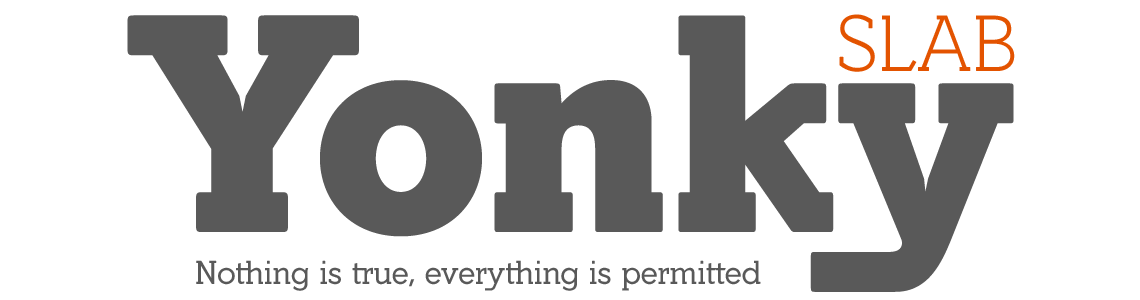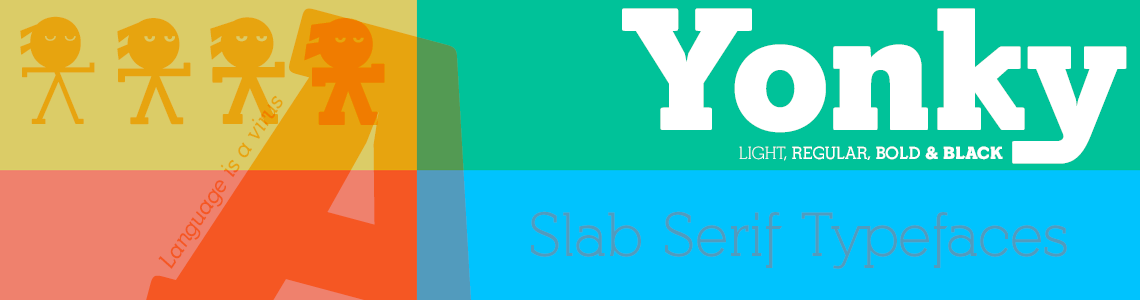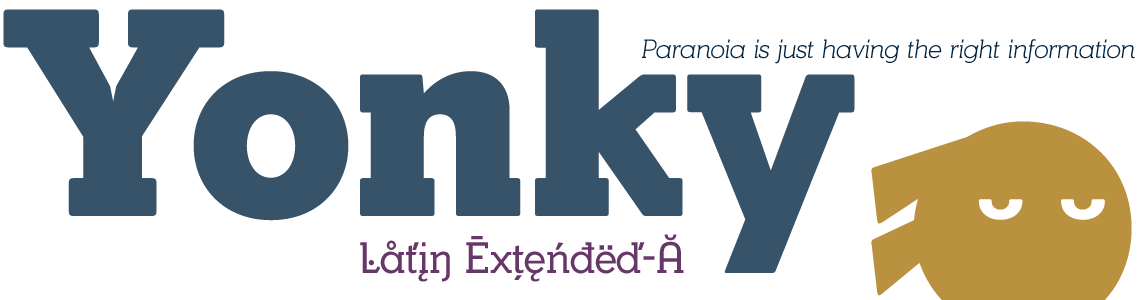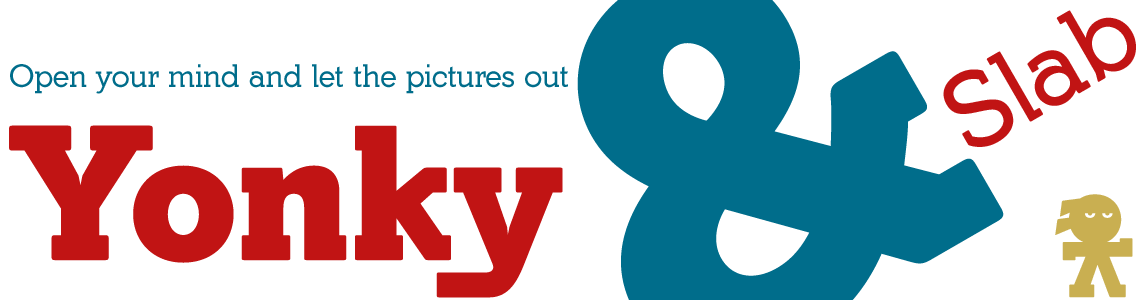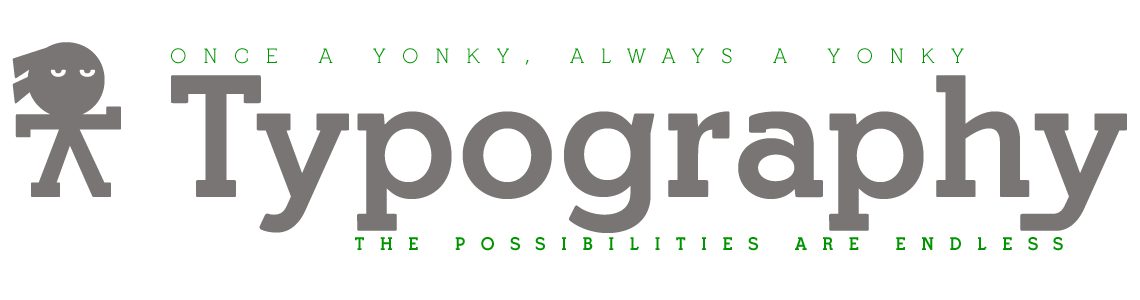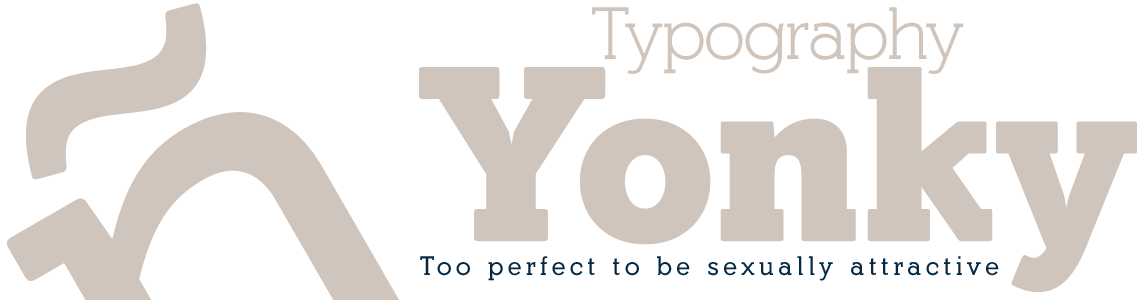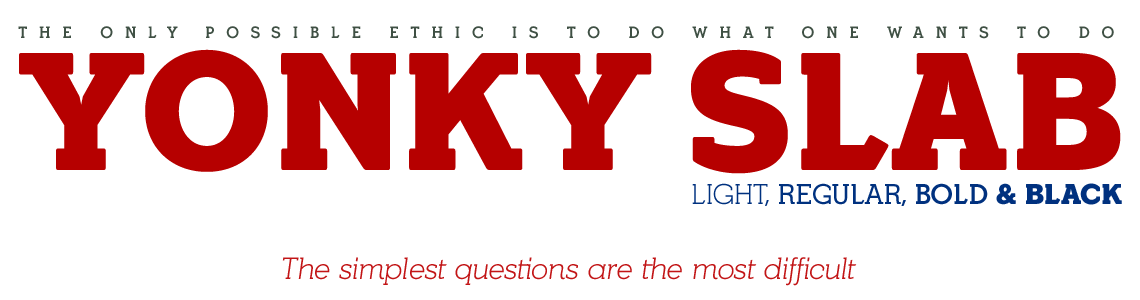
Estilo: Slab Serif, Geométrica, Corporativa
Proporción: Light, Regular, Bold, Black & ItalicS
Glyphs: 586
Alternates: 72
Autor: deFharo
Año de publicación: 2017.
Funciones OpenType: Additional languages, All Alternates, Alternate Annotation Forms, Capital Spacing, Contextual Alternates, Denominators, Discretionary Ligatures, Extended Fractions, Inferiors, Kerning, Localized Forms, Numerators, Oldstyle Figures, Ordinals, Scientific Inferiors, Slashed Zero, Stacked Fractions, Standard Ligatures, Subscript, Superior letters, Superiors, Superscript, Titling alternates.
Tipografías corporativas para diseñar títulos publicitarios rotundos o elegantes sobre cualquier medio y también para cualquier tipo de publicación como revistas o periódicos. La métrica y el kerning los he configurado cuidadosamente para una lectura fluida tanto en frases cortas de título como en textos de párrafo.
Incluyen el símbolo del Bitcoin: b# (b # ), letras contextuales alternativas y otras funciones Open Type.
Las fuentes Yonky disponen en su versión comercial de un juego de 586 glifos (Latin Extended-A), con soporte para cualquier idioma europeo o centro europeo. Yonky Slab también incluye funciones OpenType (Compatibles con InDesign, QuarkXpress, Photoshop e Illustrator.